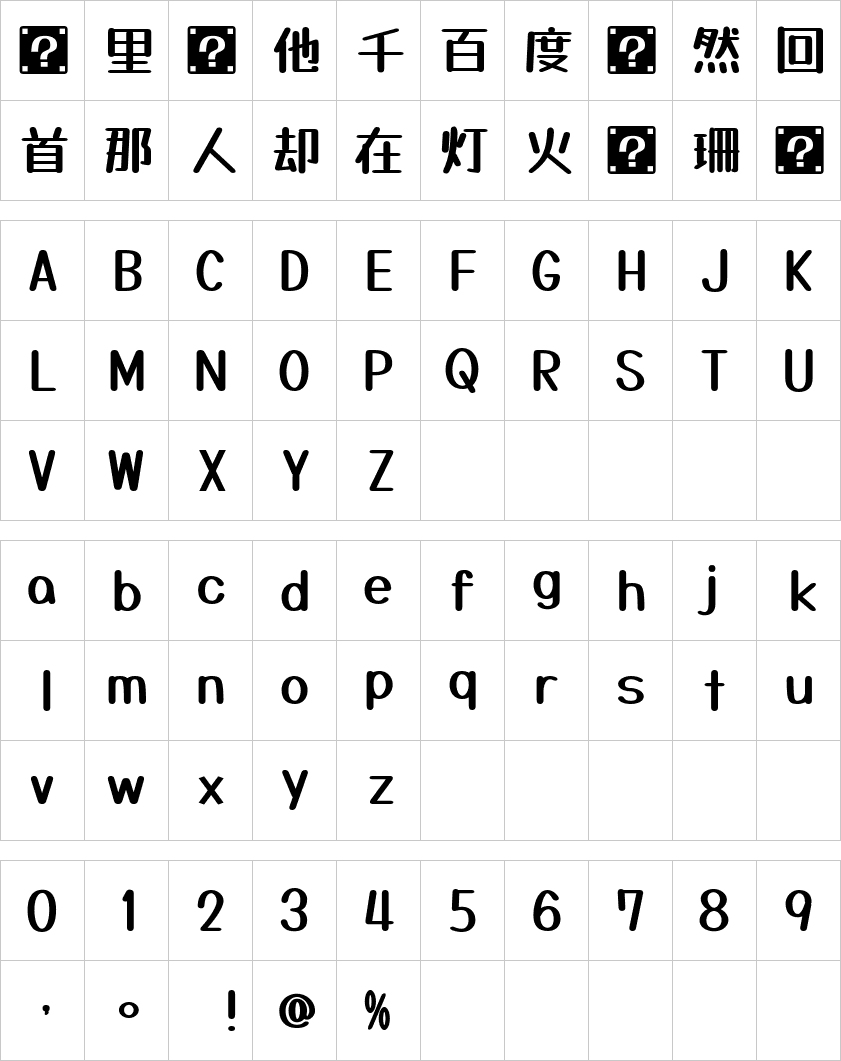
たぬゴ丸
Tanugo手写体PS字体名:たぬゴ角 / たぬゴ丸是基于之前发布的马克笔手绘体的更新版而制作的字体。Tanugo手写体保留了马克笔手绘体的特征,保持亲切性的同时,更容易使用、容易阅读。这是一款以可爱的类型设计为目标而制作的字体。
Tanugo手写体收录了平假名、片假名、字母数字、符号、到JIS第二水准的汉字以及移动IBM扩展汉字(共计7000字以上),并且有有两种样式。字体名中带“角”字的字体样式,是硬边的设计。而字体名中带“丸”字的样式,则边角是圆头的设计。